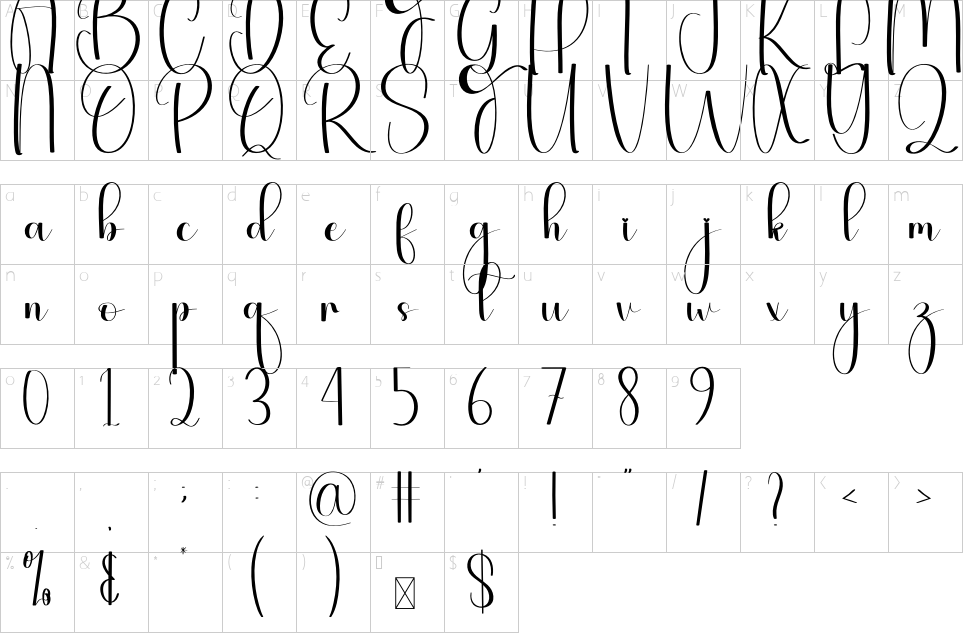
Descubra o encanto da família Santa Family, uma fonte gráfica que enriquece qualquer projeto com sua elegância e versatilidade. Desenvolvida pelo designer desconhecido William Jhordy, esta fonte é uma delicada escolha para designers e criadores de conteúdo em busca de uma opção clara e sofisticada. Com seu design cuidadosamente criado, a Santa Family combina facilmente com outras fuentes e pode ser usada em uma ampla gama de projetos, desde pequenos detalhes de design até grandes títulos em impressões profissionais. Se você é um amante de fonts gratuitas que valoriza a estética e a funcionalidade, não perca esta oportunidade de adquirir a Santa Family font para usar no seu Windows e Mac. Com apenas 617 downloads, você se junta a um seleto grupo de criadores que já encontraram a perfeição em sua forma. Descubra o charme da família Santa Family e faça seu trabalho soar ainda mais sofisticado.